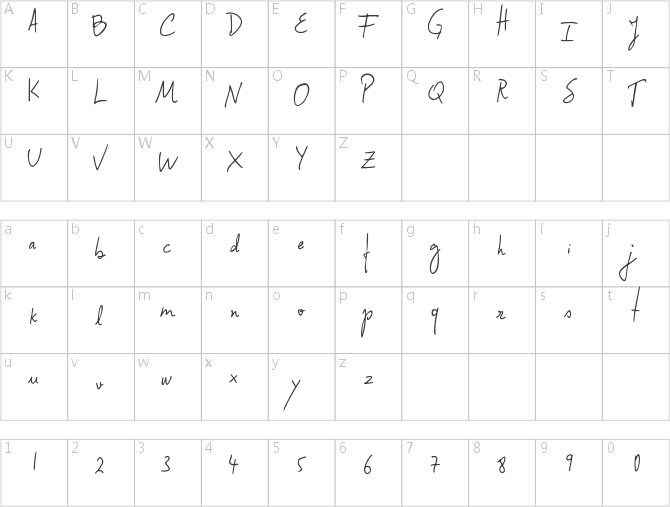
字體名稱: Confess
Confessions WITHOUT ACCENTS (Tru
Confessions WITHOUT ACCENTS (Tru字體字庫是一款讓人賞心悅目、百看不厭的英文字體,適合各類廣告和產品包裝設計應用,字體大小0.03MB,格式為ttf字體,上傳用戶是雅迪,作者/版權方為未知